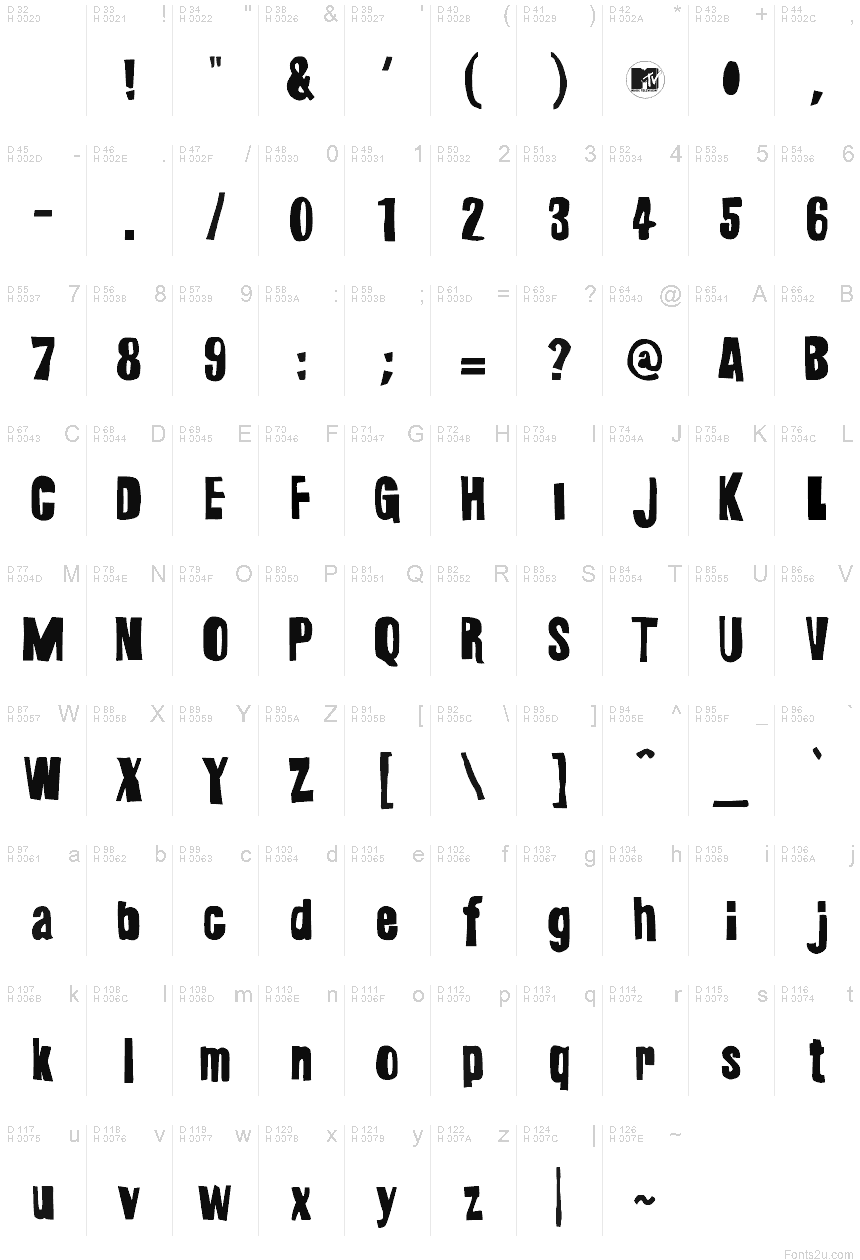
Grunge Bold
Grunge Bold, zaprojektowany przez Ryana Brotherstona, to darmowy krój pism ekspozycyjnych w stylu kreskówkowym z masywnymi, nieregularnymi literami i sylwetką wyciętą ręcznie. Jego wysokie formy wydają się celowo przekrzywione.
Zakorzeniony w liternictwie komiksowym i animowanym, nadaje się do rozrywki dla dzieci, grafiki gier i zabawnych plakatów imprezowych. Nieregularne krawędzie i zmienne szerokości sprawiają, że każde słowo wygląda na narysowane, a nie złożone, co może pomóc opakowaniu przekąsek lub marce zabawek zyskać swobodny i żywy charakter. Obok grafik postacianych lub prostych bazgrołów tępe krzywe i krzywe kontury mogą stać się częścią samej ilustracji zamiast służyć jako neutralne napisy, nawiązując do swoich szerokich kształtów i komiksowej przesady.